おすすめの手描き風英語フォントを紹介します。
ロゴや見出しにも使えるバランス感のあるフォントから、カンバスに書きなぐったようなインパクトのあるフォントまで、おすすめのフォントです。
Brizzush
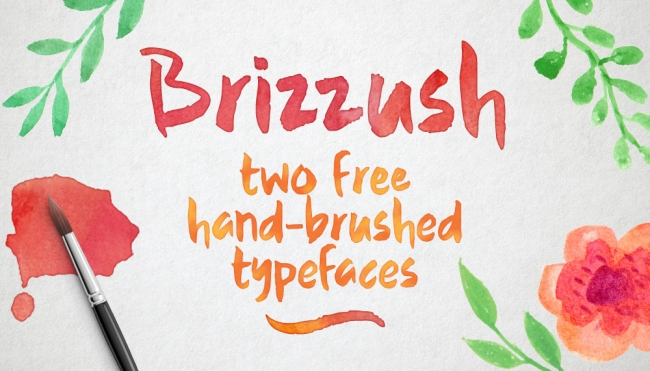
Brizzush
水彩ブラシで描いたような、柔らかい印象の手描き風フォントです。ラインが滑らかなタイプと荒いタイプ、2種類のバージョンが用意されています。
Serendipity Script Free Font
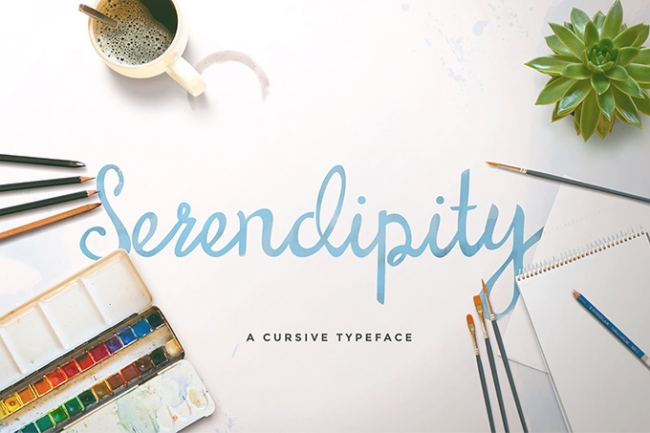
Serendipity Script Free Font
ロゴや見出しに使いやすい、バランスの取れた手書きフォントです。筆でサラサラと描いたような、軽い印象が素敵です。
Carosello Font
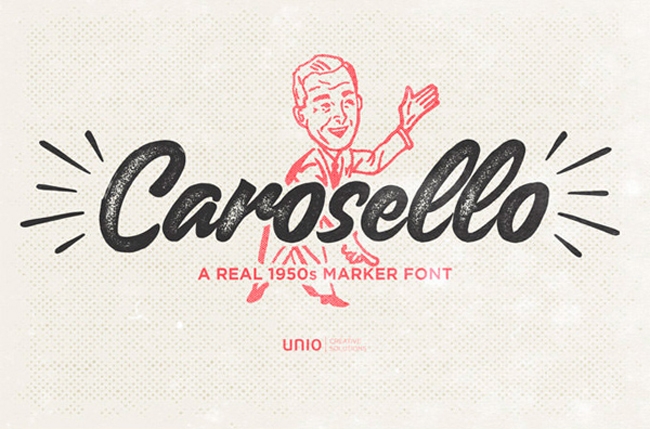
Carosello Font
レトロで美しい英字フォントです。ヴィンテージ感のある手描き風のフォントで、広告のデザインなどに使えます。
Arkana Script Vintage Font
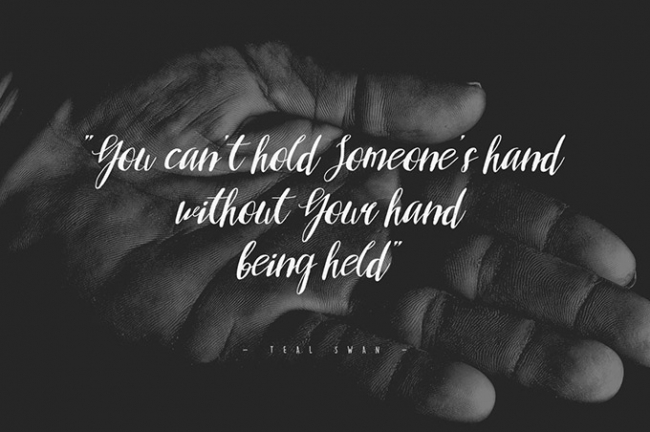
Arkana Script Vintage Font
エレガントな筆記体フォントです。少しヴィンテージ感があり、デザインに深みが出ます。
FOFER Handwritten Font
Wayward
Westchester
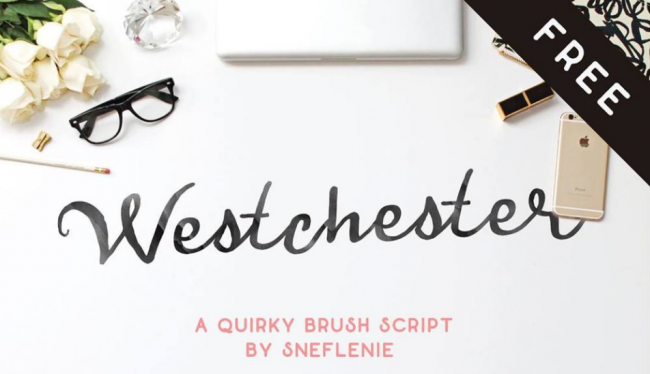
Westchester
Ambarella
Pilsner + Gutenberg
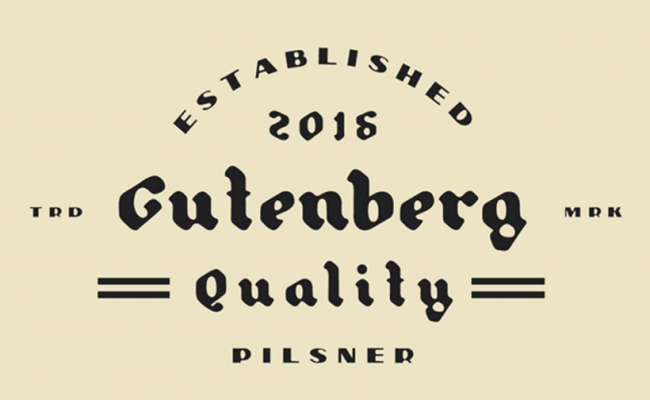
Pilsner + Gutenberg
Againts Typeface
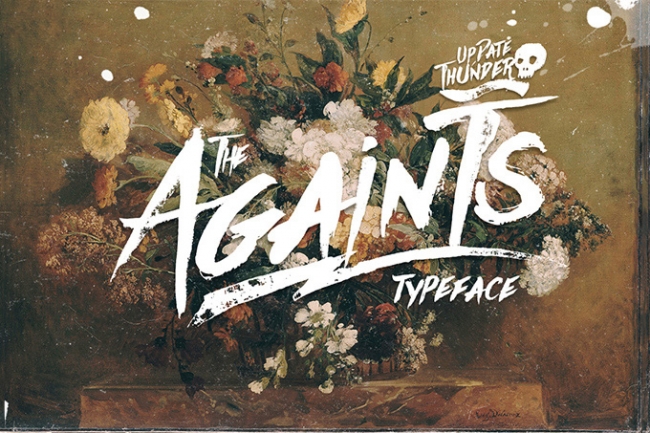
Againts Typeface
キャンバスに書きなぐったような、力強さのある英字フォントです。デザインにインパクトを出したいときに使えます。
BRUX BOLD BRUSH FONT
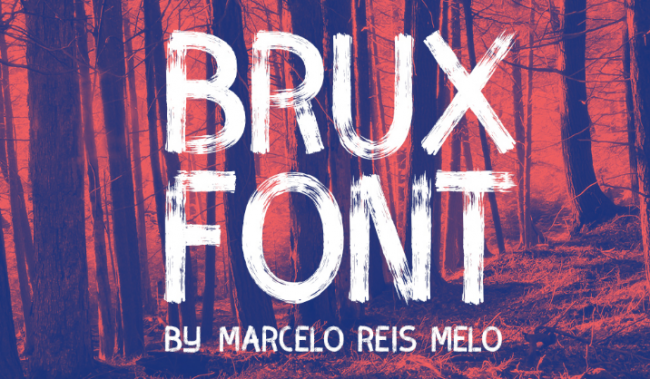
BRUX BOLD BRUSH FONT
Ludicrous
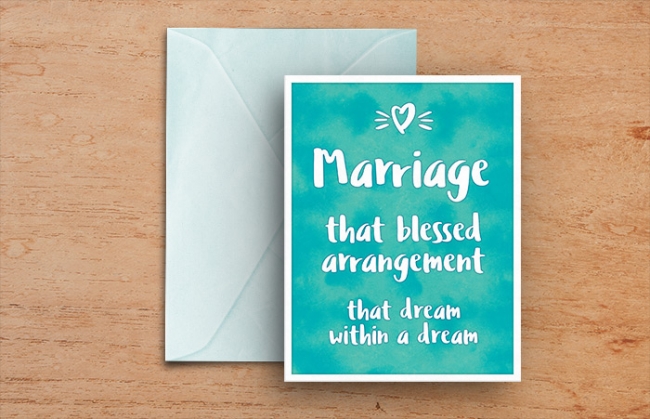
Ludicrous
ポストカードのデザインに合う、少しポップな印象の英字フォントです。
Foxhole Hand Drawn
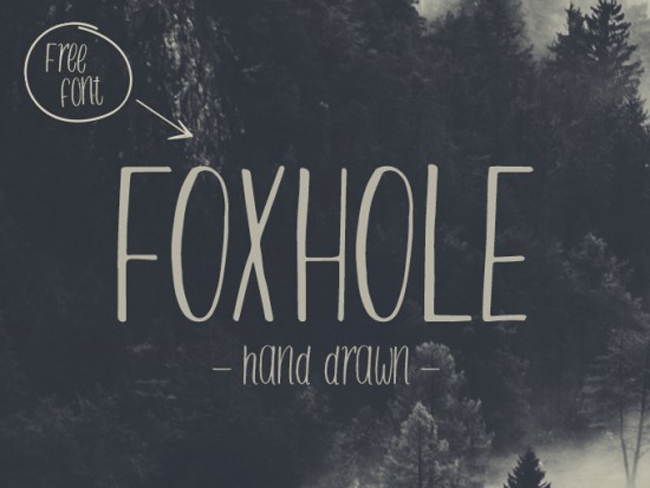
Foxhole Hand Drawn
手書きのサンセリフフォントです。シンプルで、使いやすいデザインです。